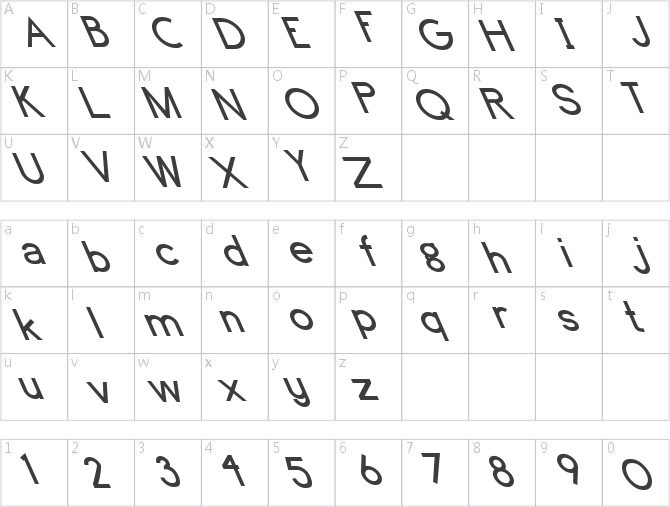
Brassfield Extreem Lefty
Brassfield Extreem Lefty介紹
Brassfield Extreem Lefty字體字庫是一款讓人賞心悅目、百看不厭的英文字體,適合各類廣告和產品包裝設計應用,字體大小0.03MB,格式為ttf字體,上傳用戶是志誠設計,作者/版權方為未知